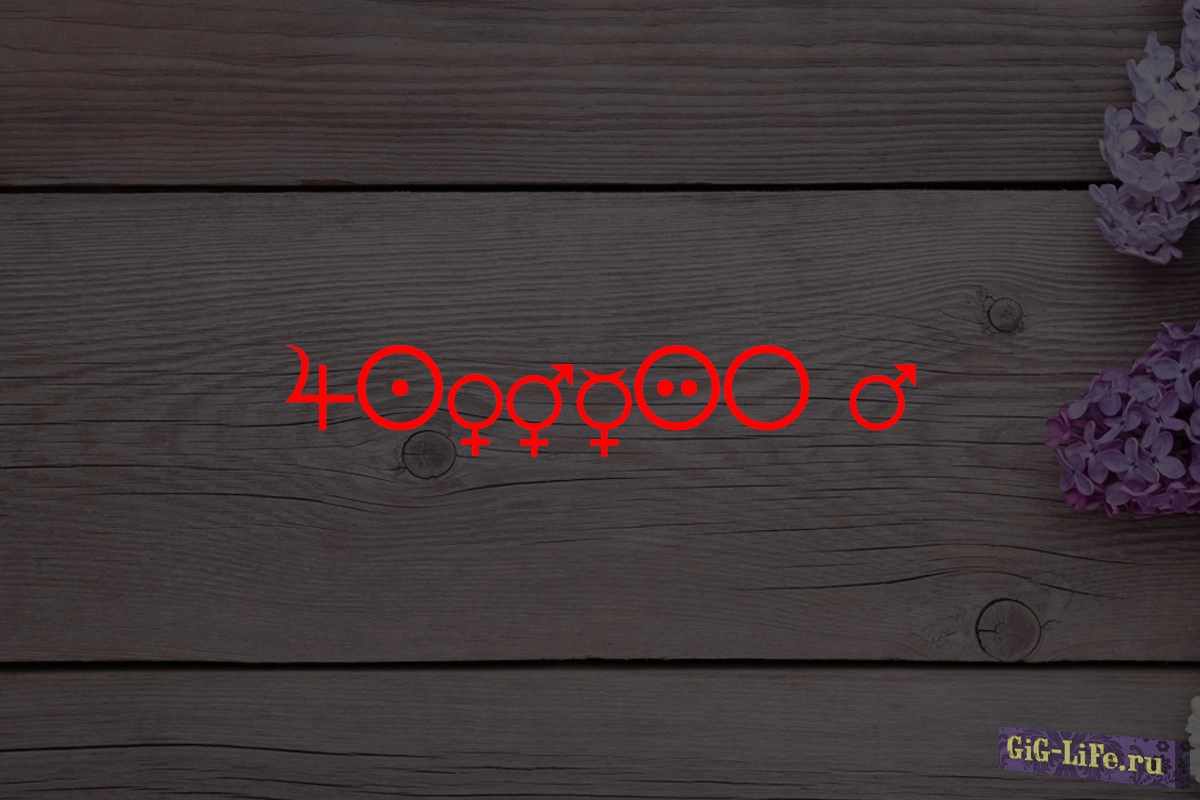
FrazettaBatsTest1 - это эротический шрифт, созданный специально для использования в Photoshop и других творческих проектах. Он включает в себя 4 уникальных символа.